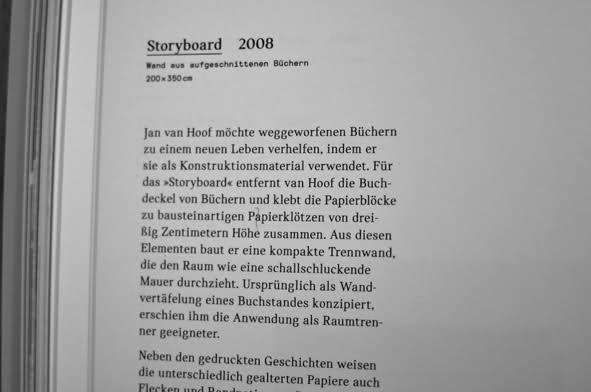
noch eine Schriftsuche ..
ich bin auf der suche nach folgender schrift – wtf konnte mir da nicht weiter helfen.
leider konnte ich mit meinen 50mm nicht näher ran, ich hoffe es reicht.
mmh, sieht bisschen wie eine Barock-Version der Ambroise von Porchez aus oder Didot Elder von Optimo mit weniger Kontrast und nicht-klassizistischen Formen.
Aber sie hat das typische Vibert-g. Vielleicht hilft Dir das beim googlen (der war Schriftschneider bei Didot)
Kannst Du vielleicht etwas über die Quelle sagen? Mir kommt es so vor, als hätte ich dieses ›g‹ kürzlich schon einmal gesehen …
Der famose Patrick hat's gewusst. Es ist die Catalog von Binnenland.ch
Aber wenn ich die jetzt so im Detail sehe, will ich sie am liebsten gleich wieder vergessen.
Ah, richtig. Und jetzt weiß ich auch wieder, wo ich die Schrift
schon gesehen habe: Es ist die Hausschrift des Magazins ensuite.
Florian, ich bin in dem buch "un/folded" über das "g" gestolpert.